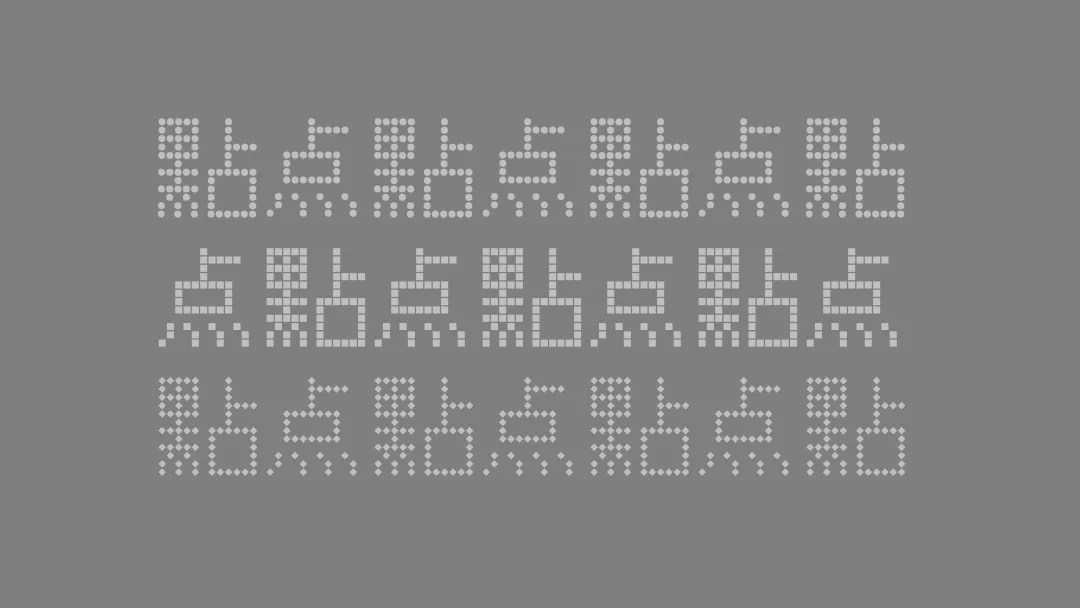
「點點像素」是基於同樣以GPL 2.0協議開源的自由字體「文泉驛點陣宋體」,經自動矢量化轉換,變形和美化得到的,涵蓋超過22000字形的大字符集中文像素藝術字體。「點點像素」使用的將點陣字體自動轉換為OpenType字體的源代碼也已開源。
目前可見的中文像素藝術字體大多有商業許可協議保護,且很多無法涵蓋GBK字符集中的全部漢字字形。「點點像素」及其轉換工具提供了從開源點陣字體生成開源像素藝術字體的另一種可能。
前幾天我為我們舉辦的DeeCamp人工智能訓練營設計宣傳海報的時候,想走復古風,用像素藝術字體來寫主要的宣傳語。發現網上可找到的一些像素字體,往往都有商業許可協議的保護,或者在製作上只包含GB2312這樣的基礎字符集。
程序員就喜歡自力更生。就動手寫了一個JavaScript轉換工具,基於著名的開源字體項目「文泉驛」創建的點陣宋體漢字(目前用的是10pt字型的版本),自動完成所有22000多個字形的矢量化,自動將點陣像素變形為不同修飾風格。
代碼寫得比較簡單。目前發佈的v0.1版本的「點點像素」字體只能說初具像素藝術字體的基本模樣,大體可用,但後續還有很多優化空間。之後有時間時,會繼續優化這個項目,用自動化代碼創建更多有趣的字體。